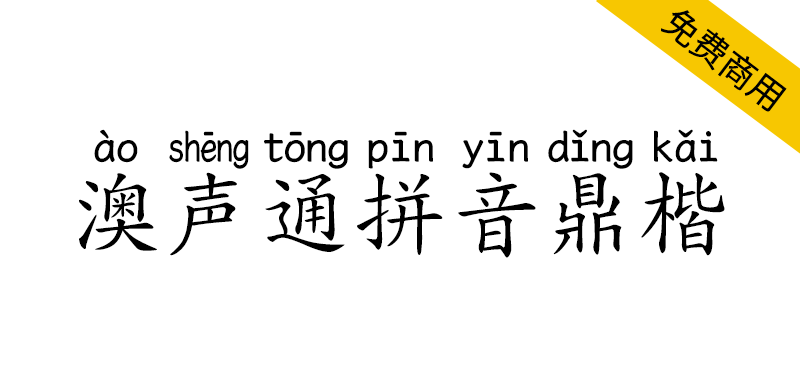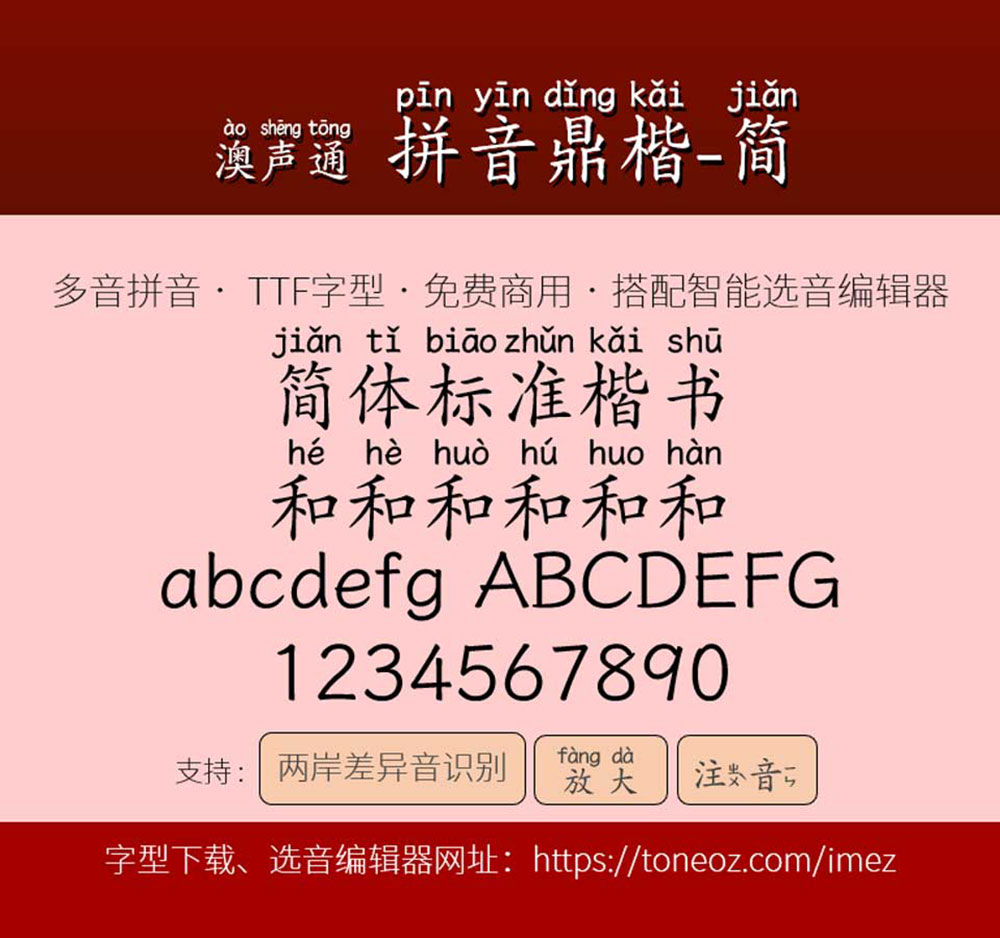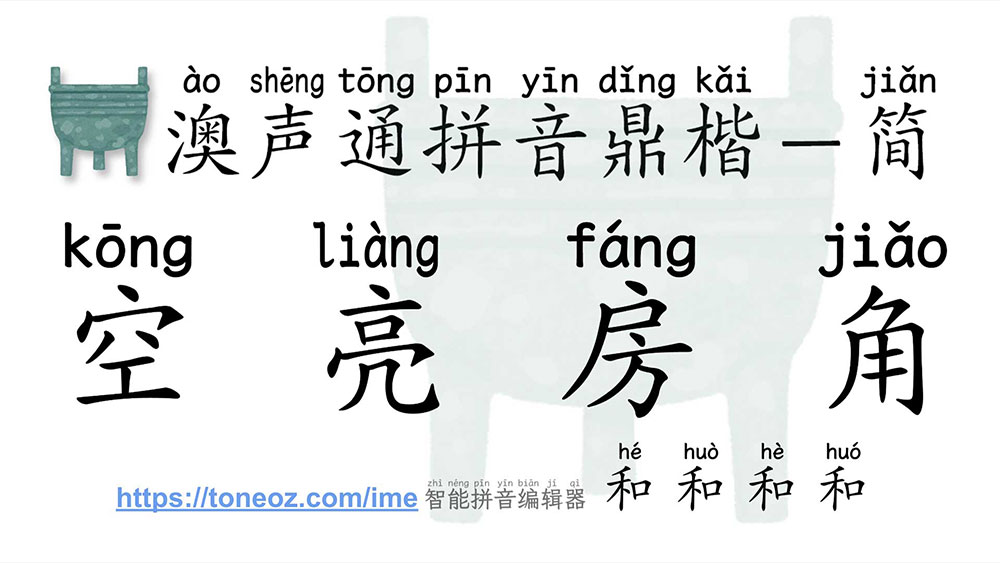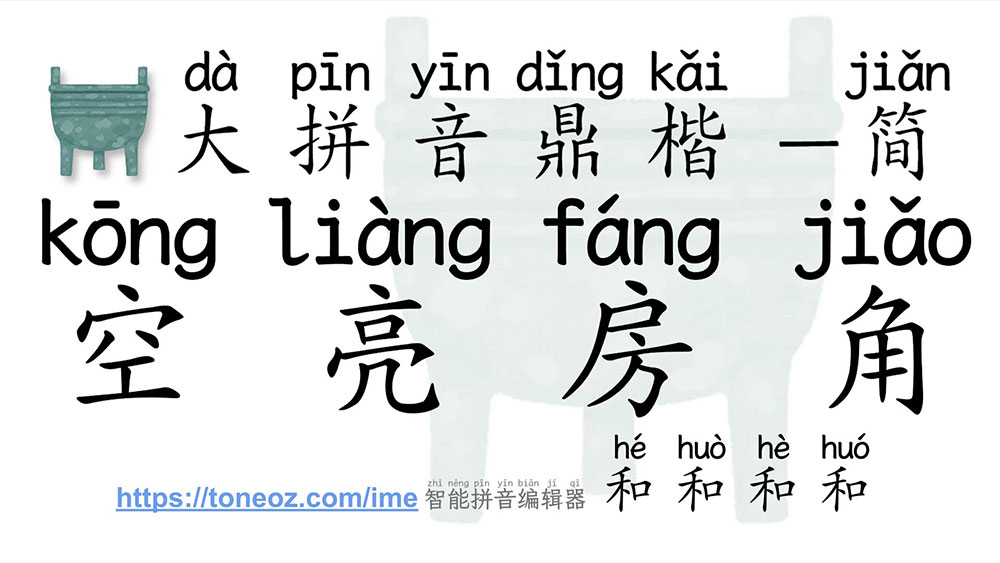
澳声通拼音鼎楷是一款基于文鼎PL简中楷的可选多音字的TrueType楷体拼音字型,满足中文现场教学需求,搭配国际标准《ISO 7098中文罗马字母拼写法》的汉语拼音字型,适合熟悉罗马字母的学习人士。
标准版(小拼音版)的大小适当不影响字距,适合文章阅读或试卷,大拼音版本适合投影片或标题。每个字的拼音宽度不同,最短的只有一个字母,最长的字「装zhuāng」有6个字母,大拼音字型的拼音此时可能会重叠,使用者可利用字距或者加入空白来调整。
一、澳声通小拼音鼎楷(ToneOZ-Pinyin-Kai-Simplified)